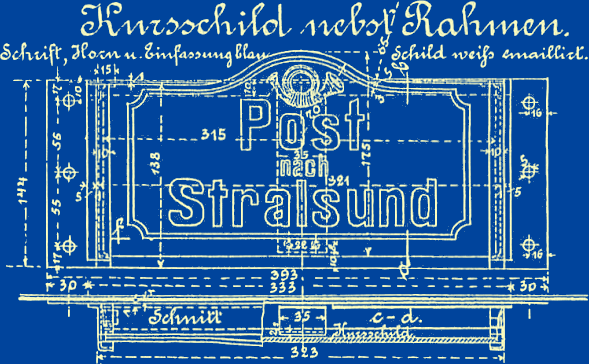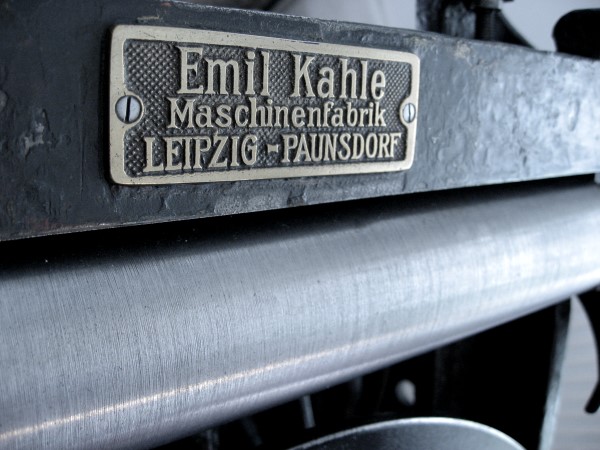
Schrift passend zum Thema Maschinen?
Ich suche Schriften passend zum Thema Maschinen. Sowohl Brotschrift für mehrspaltigen Fliesstext als auch für grosse Überschriften.
Irgendwelche Ideen?
Das habe ich mich eben auch gefragt. Trotzdem – ohne das zu wissen einfach mal spontan:
Serif
• Richler
• JAF Lapture
• GT Sectra
(etwas weg vom Klischee)
Sans
(eher dran am Klischee)
Was für Maschinen denn?
Die entscheidende Frage.
Ein Golem? Eine Spieluhr? Ein Atom-U-Boot? Eine Wassermühle?
Ich glaube, wenn es ganz allgemein um Mechanik geht und vielleicht um Kraftübertragung, gibt es keine besonders geeignete Schrift dafür, weil diese angewandten physikalischen Gesetze älter sind als die Schrift. Wassermühlen gab es schon vor über 2000 Jahren. Drehbänke sind vor über 5000 Jahren verwendet worden. Den Abakus, die Rechenmaschine mit den Kugeln, gab es schon 1000 Jahre vor Christus.
Also das Stichwort reicht nicht aus. In welcher geistigen Welt sind die Texte angesiedelt? Das Thema müßte eingegrenzt werden. Die Maschine in der Kunst (Wunderkammern), die Industriemaschine, der Haushaltshelfer, die Entstehung der Naturwissenschaft, die denkende Maschine (Computer) usw. usf. Man kann mit jeder guten Leseschrift eine entsprechende Atmosphäre durch Anordnung (zum Beispiel »Mechanisierung des typografischen Bildes«) und Illustration (Ornament, Rahmen, Bild) schaffen. Die Raumaufteilung und typografische Ordnung wirkt stärker als die Schrift selbst.
Maschinen gibt es seit Jahrtausenden, die serifenlose Schrift haben wir seit rund 200 Jahren im Einsatz, und seit 200 Jahren wird sie für »modern« gehalten. Die Handbücher neuerer Maschinen sind wohl durchweg mit solchen Schriften gesetzt worden, Helvetica, Univers, und sie wirken allesamt eben wie irgendwelche Handbücher für irgendwelche Maschinen unserer Zeit. Das sind keine Texte, in die man sich vertiefen möchte.
Und noch ein Gedanke:
Ist es zwingend, die Serifenlose für besonders geeignet für Maschinen zu halten? Und wenn ja, warum? Nehmen wir die Maschinen des 20. Jahrhunderts. Ich hab mich nie in diesen Fragen belesen und rede ins Blaue: Die Formen der älteren Maschinen in meiner Werkstatt sind nicht nur funktional, aber die Anpassung der Form an die Funktion scheint mir verschieden stark. Das Schwungrad meines Pedaltiegels, gebaut um 1900, hat zwar gerade Speichen, aber diese Speichen sind keine runden Stangen, sie sind »schön« geformt. Die Kolben und Wellen sind rein funktional, aber das Fundament und die Füße haben Schwünge. Ebenso der Heidelberger Tiegel. Das ältere Modell (1952) hat noch etwas mehr Rundungen. Eigentlich ist die Maschine schwarz, das neuere Modell (1969) hat an der Seite eine mittelgraue Verkleidung, deren Form allerdings so sorgfältig an das dahinterliegende Schwungrad mit dem Keilriemen angepaßt wurde, daß sie als schön gelten kann. Meine Schneidemaschine, nach 2000 gebaut, ist hellgrau und scheint mir rein funktional geformt, ich sehe jedenfalls keine Anzeichen, so etwas wie eine schöne Form durch zusätzliche Bemühung um Formgebung zu erlangen. Ich habe aber auch noch eine kleine Ösmaschine, die durchaus eine schöne Form hat, gebaut nach 2010. Diese kleine Maschine hat gewölbte Formen, die nicht rein funktional nötig sind.
Die Serifenlose ist nur auf den ersten Blick und für den Unkundigen eine rein funktionale Schrift. Wenn sie rein funktional wäre, brauchte man nur eine. Aber jede gute Schrift ist darauf aus, den Leser nicht zu ermüden. Auch die Serifenlose hat im besten Fall schöne Formen. Sie unterliegt denselben Bedingungen wie jede andere Schrift auch. Edward Johnston hat das mal definiert in fünf Gesetzen:
1. zeige sie keine überflüssigen Striche.
2. seien die unterscheidenden Kennzeichen der Buchstaben deutlich ausgeprägt.
3. trete kein Glied eines Buchstaben unberechtigt vor oder zurück.
4. bilde jeder Buchstabe ein einheitliches organisches Ganzes und nicht nur eine Ansammlung einzelner Teile.
5. stünden die zueinander gehörigen Glieder gleichmäßig miteinander in Einklang.
Wenn es eine Schrift gibt, deren Funktion im Entwurf eine stärkere Rolle spielt als ihre Lesbarkeit (und also Schönheit), also die Form einer anderen Funktion als reiner Lesbarkeit untergeordnet ist, dann ist das beispielsweise eine Proportionalschrift (Schreibmaschine) oder eine Schablonenschrift (technisches Zeichnen). Für Überschriften kann man in einem Magazin mit solchen »unschönen« (zumindest weniger schönen) Schriften durchaus eine technische Atmosphäre erzeugen. Aber Achtung, das gilt eben nicht für alle Zeiten, denn auch Baupläne, beispielsweise, waren noch vor hundert Jahren kunstvoll gezeichnete und geschriebene Blätter. Es gab vor ein paar Monaten im Berliner Gropiusbau eine Ausstellung über junge sowjetische Architektur. Die Bauzeichnungen waren zugleich Kunstwerke mit sorgfältig gezeichneten Schriften. Die Darstellungen von Mauerwerk waren Stein für Stein getuscht, um die Lebendigkeit des Baumaterials zu zeigen.
Tja, es kommt wirklich auf die Art der Maschinen an – Mechanik oder Elektronik? Zahnrad oder Platine? Geht es um eine nostalgische Betrachtung alter Dampfmaschinen oder um Hightech? In Schriften gedacht hätte ich da zu den einzelnen Optionen doch sehr unterschiedliche Assoziationen …
Also im Maschinenbau ist die Arial sehr verbreitet. Immer ist die Begründung:
• Die hat doch jeder auf dem Rechner, sonst wird das gedruckte Handbuch net richtig angezeigt! ... uff! :zzzz: